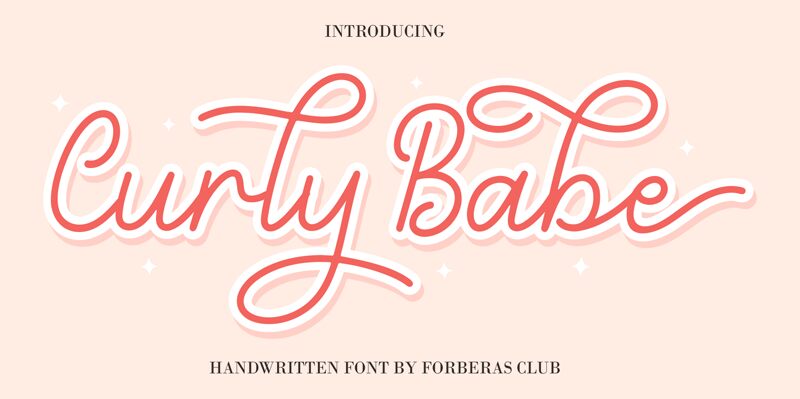
Curly Babe
Curly Babe, da Forberas Club, é uma fonte manuscrita gratuita composta por traços longos e elásticos e um ritmo cursivo solto que mantém as letras em movimento. Seus swashes de entrada altos, curvas estreitas e descendentes alongadas dão a ela um fluxo leve, semelhante a uma assinatura, diferenciando-a do salto contido de uma brush script comum.
Esse dinamismo funciona perfeitamente em logotipos de boutiques, embalagens, cartões de convite, posts para redes sociais e artes com citações onde uma linha pessoal pode carregar todo o layout. Ela também valoriza convites de casamento ou branding de beleza, especialmente quando as maiúsculas imponentes e os finais alongados recebem um pouco de espaço para respirar.